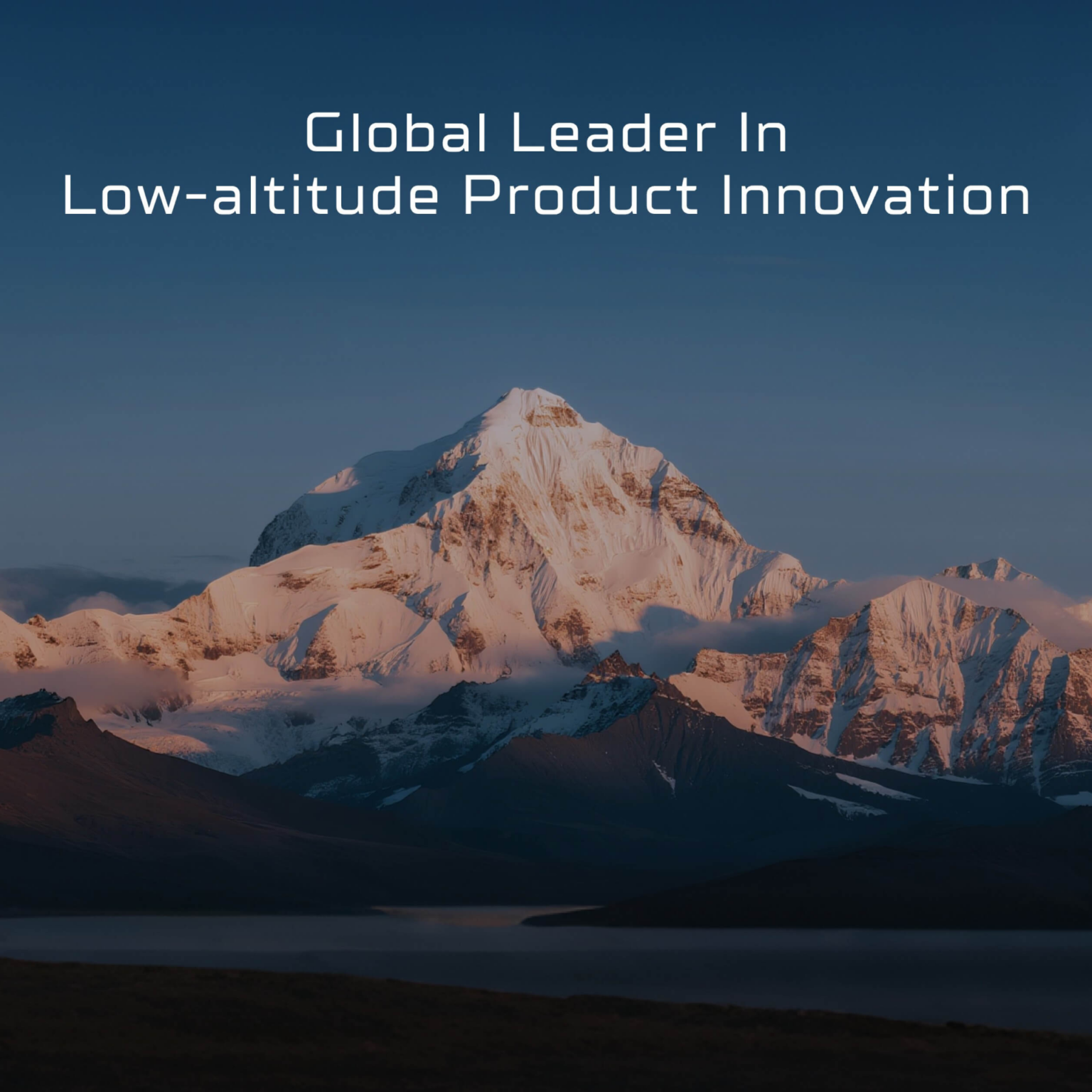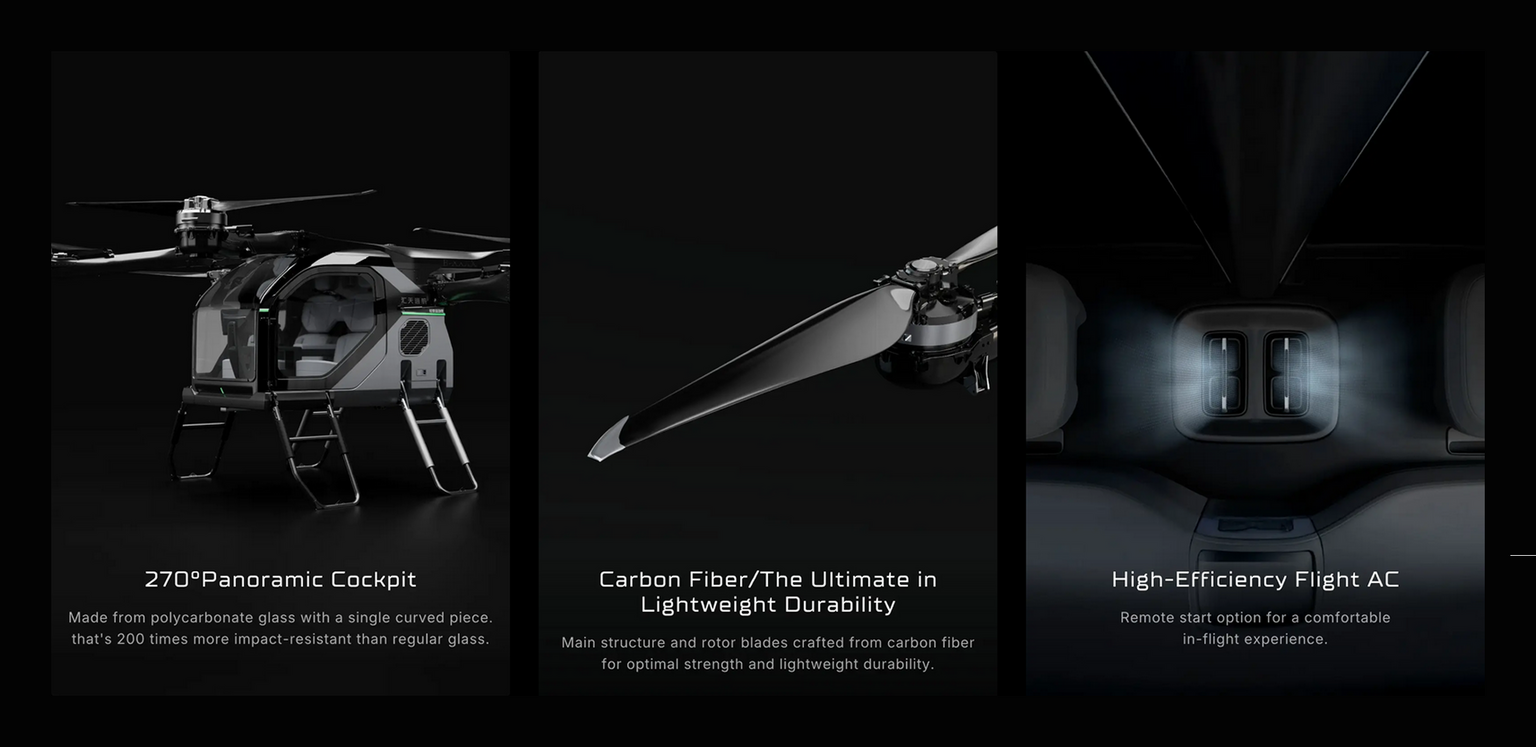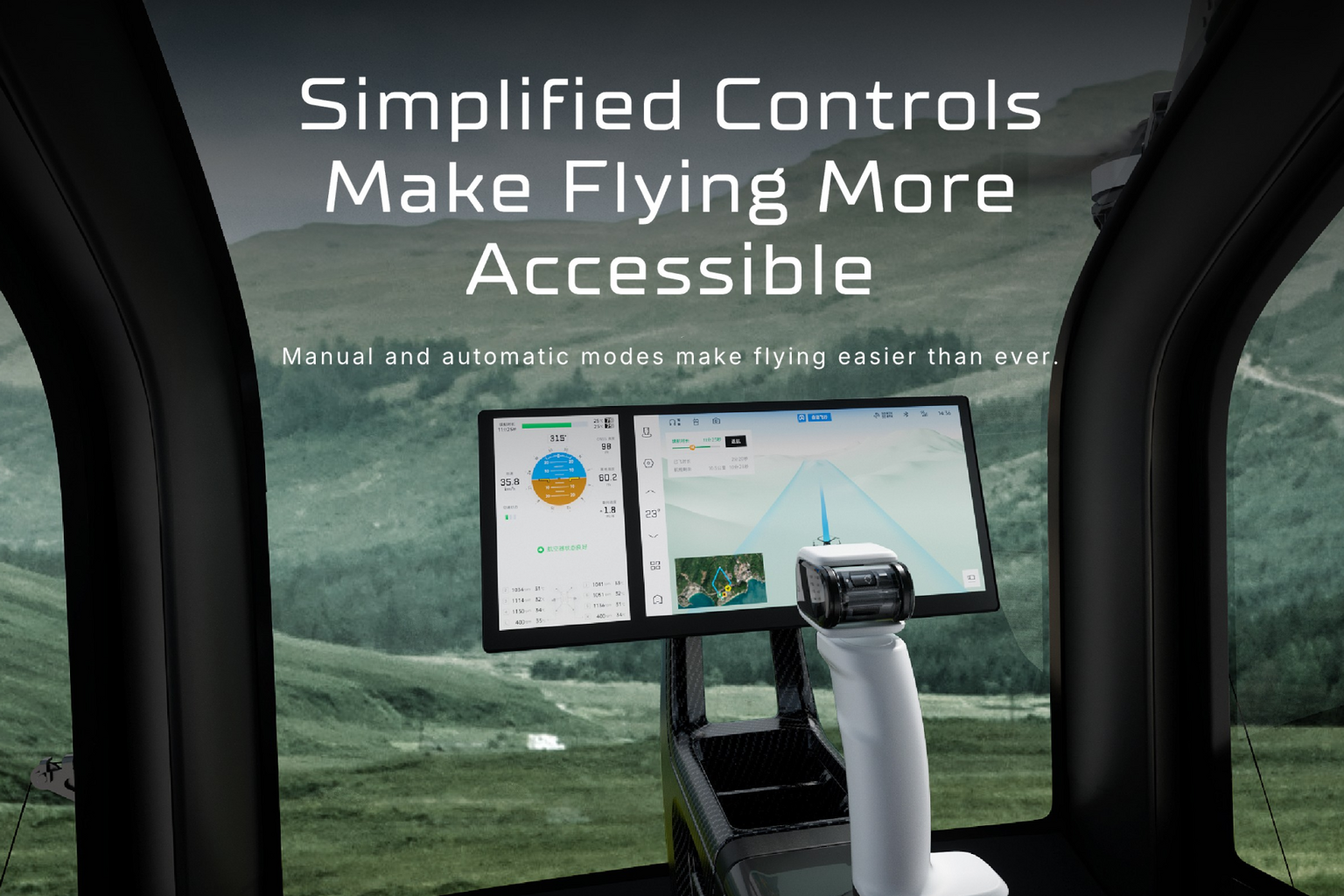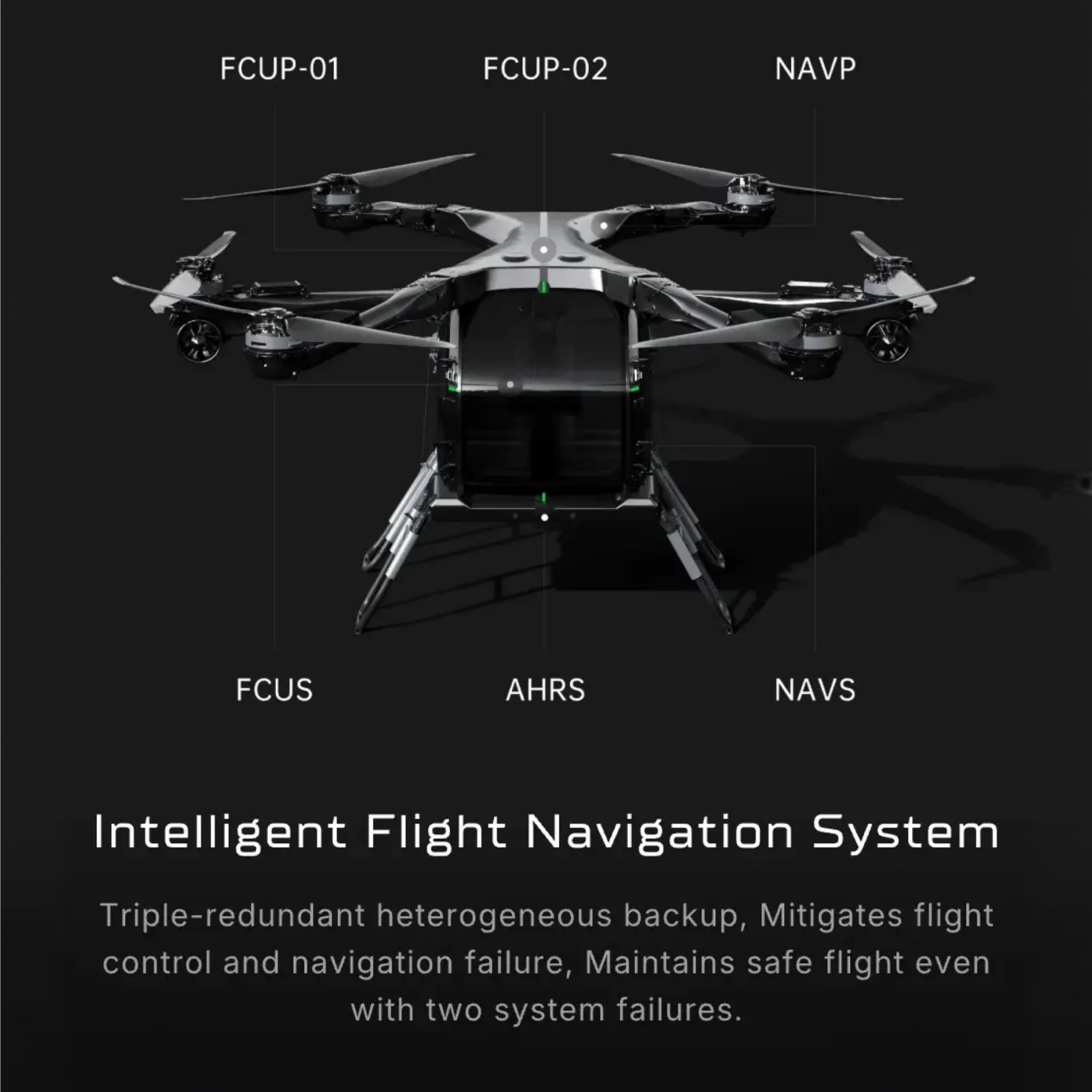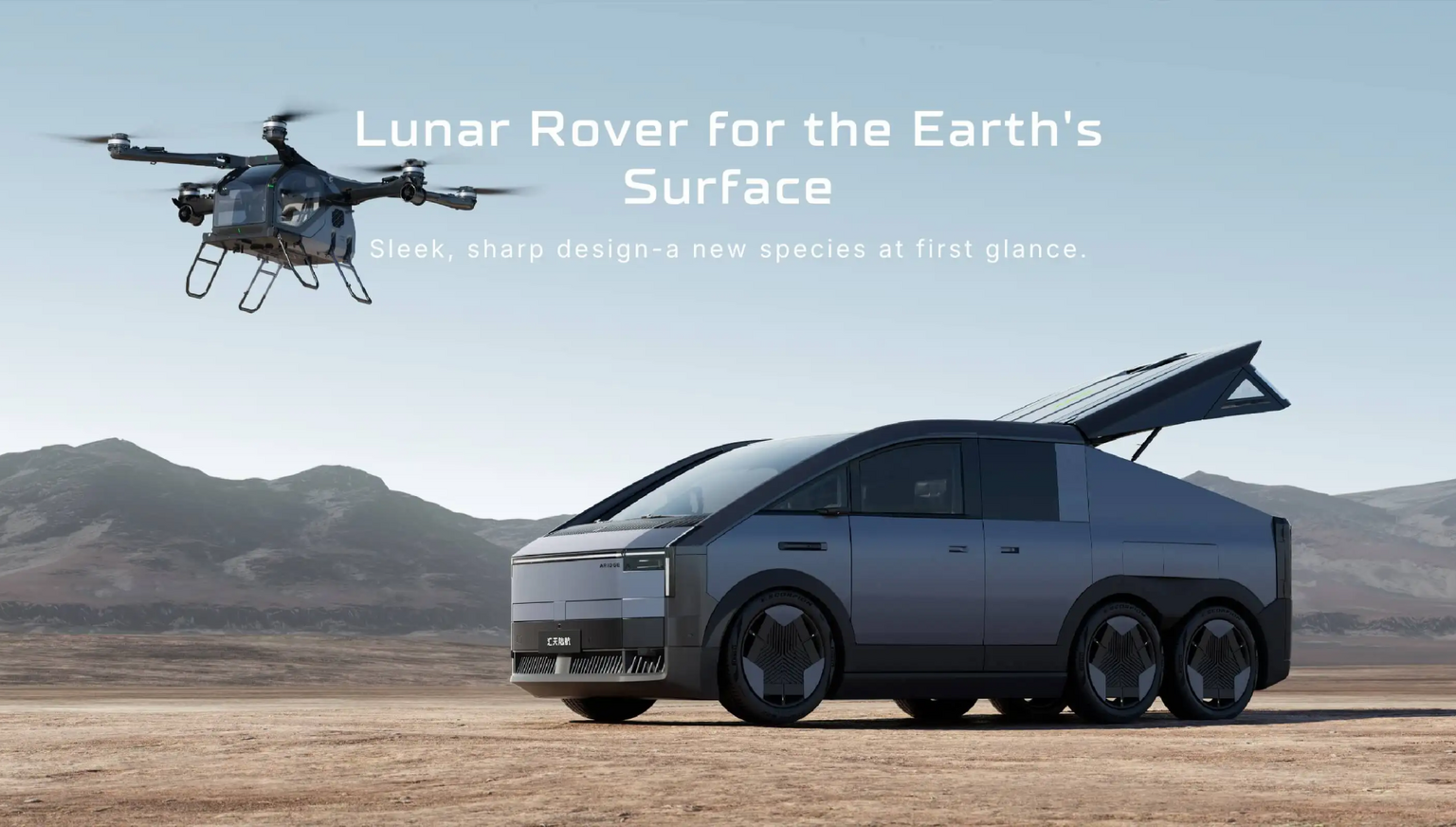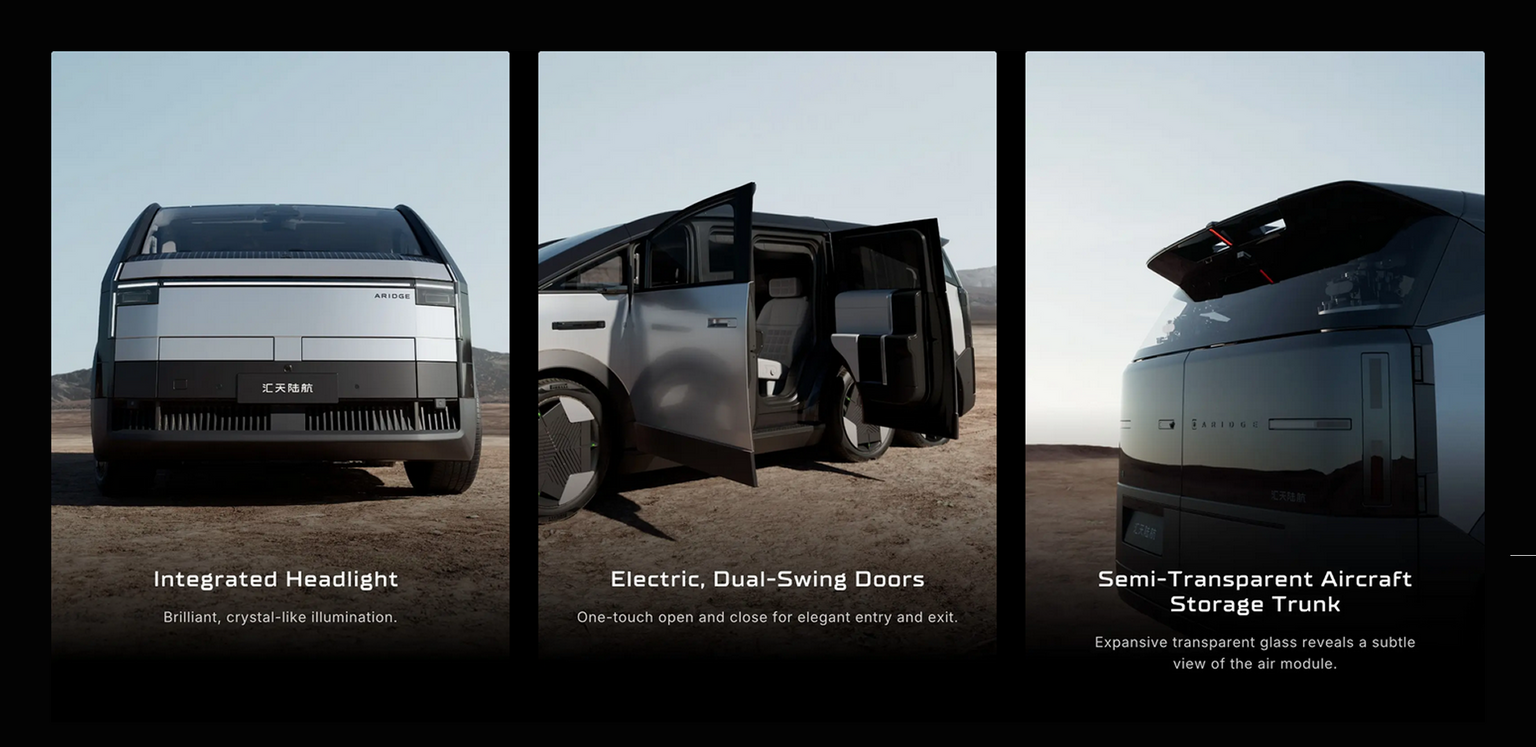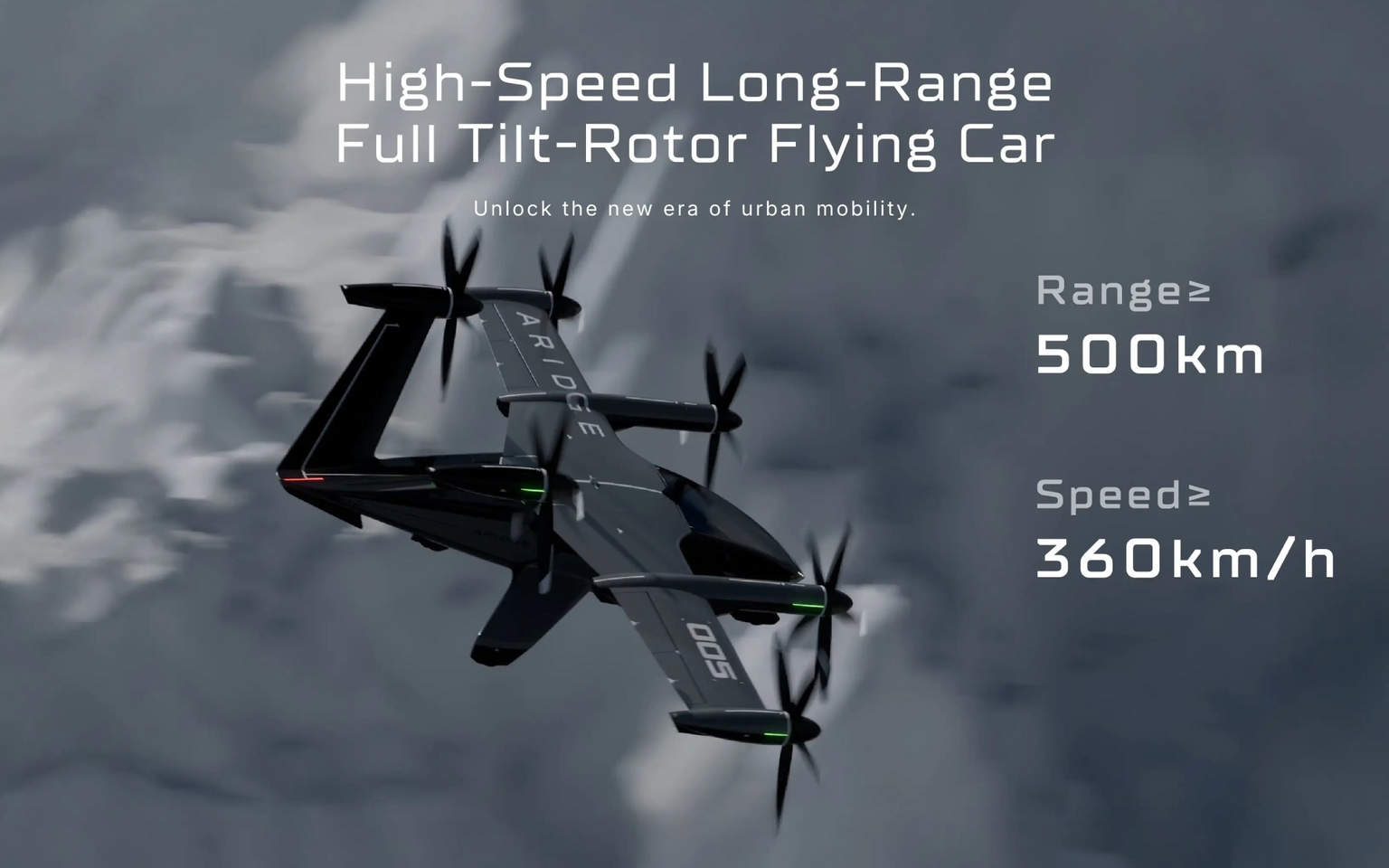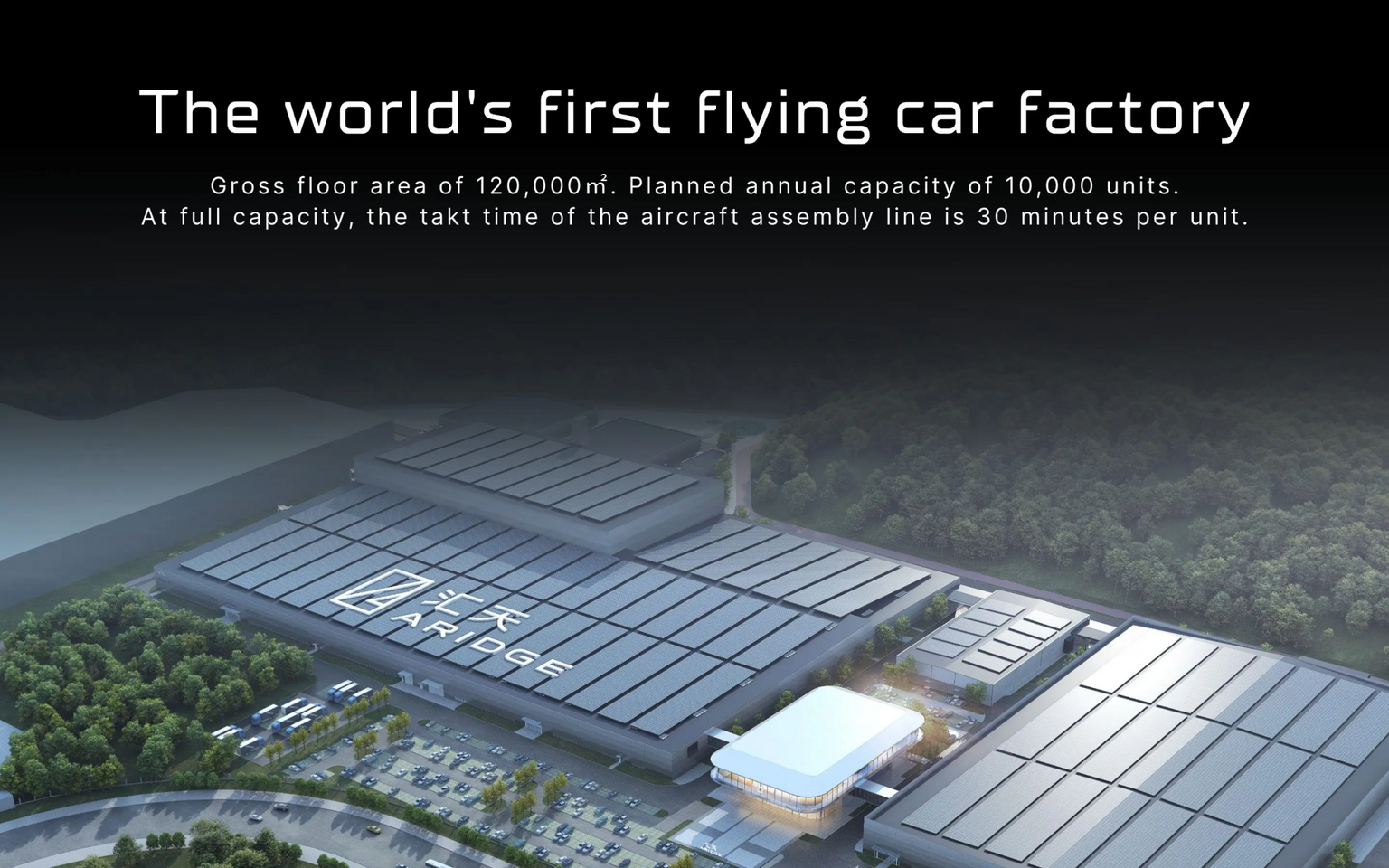
ТТ Супермолот Нью (TT Supermolot Neue) стал фирменным шрифтом компании Aridge.
Aridge — китайская компания, специализирующаяся на разработке летающих автомобилей и гибридных транспортных решений для передвижения по земле и воздуху. ТТ Супермолот Нью усилил динамичный стиль и подчеркнул высокотехнологичный образ компании.